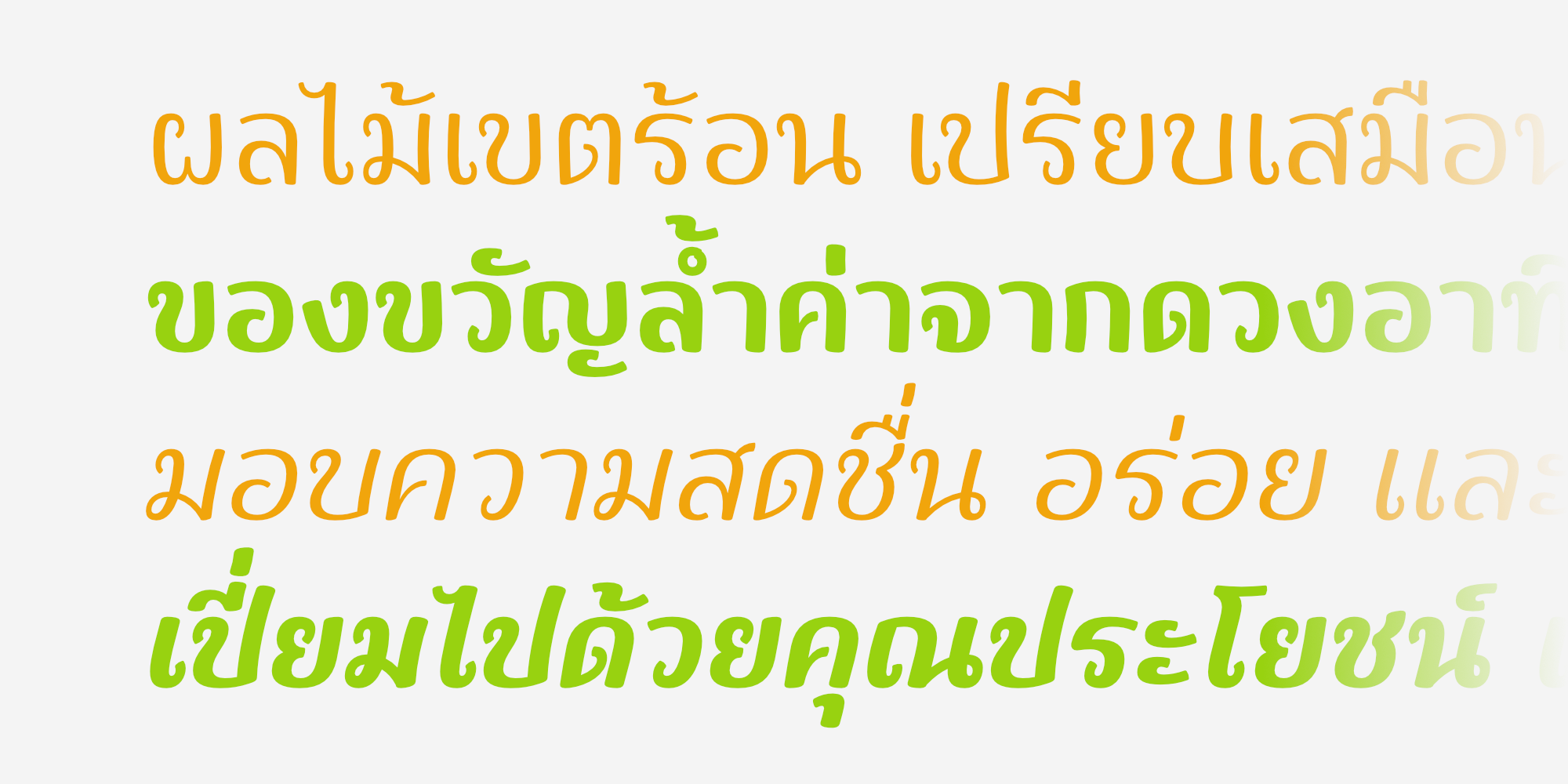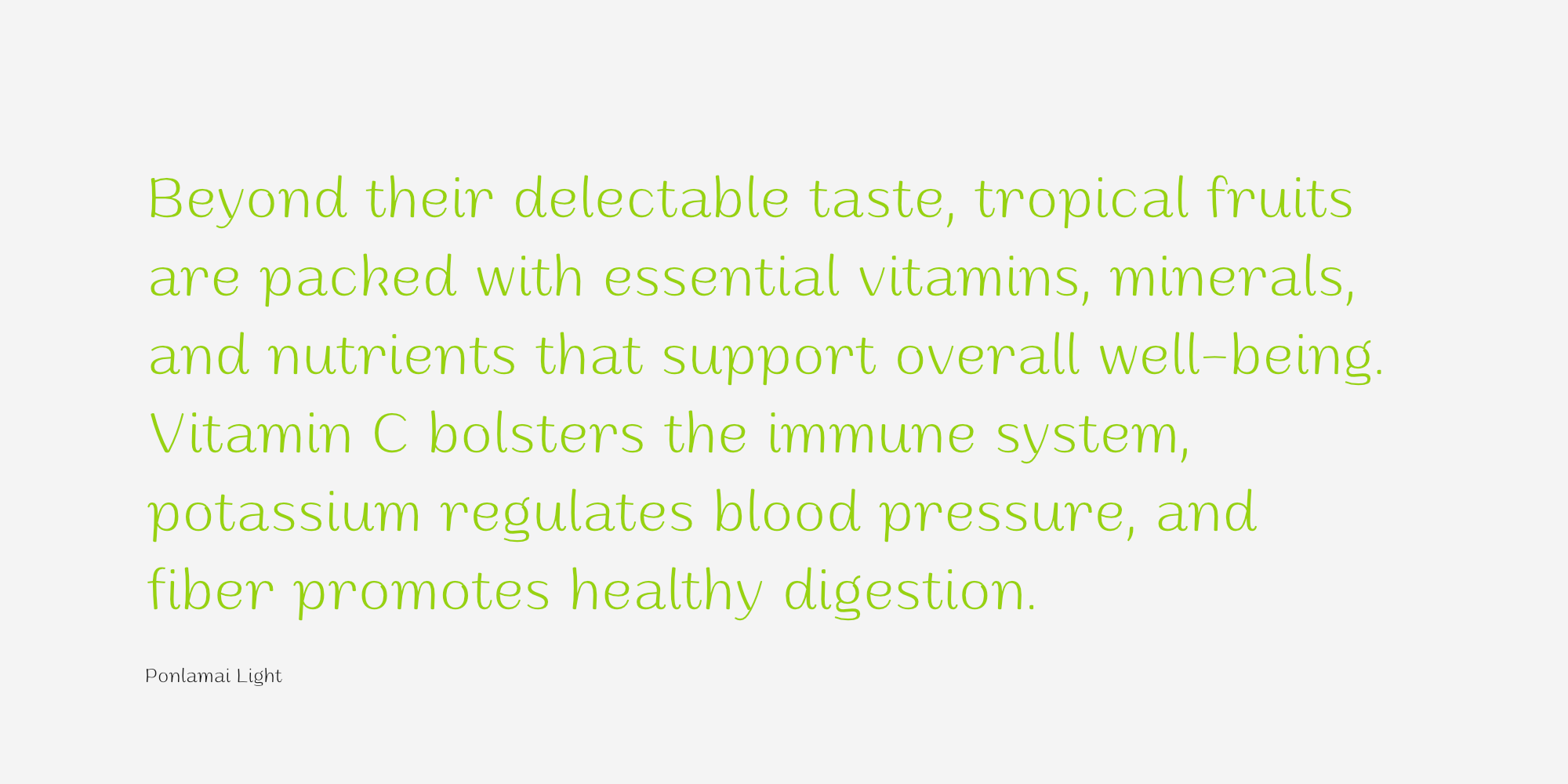
ผลไม้ | Ponlamai
ชื่อฟอนต์ : ผลไม้ | Ponlamai
Ponlamai แบบอักษรสุดชิคที่จะพาคุณเดินทางสู่ตลาดผลไม้สดแห่งความทรงจำ! เหล่าพ่อค้าแม่ค้าตลาดสดนั้นล้วนแล้วแต่เป็นศิลปินเงียบ ๆ ที่ใช้ปากกามาร์กเกอร์วาดสีสันบนป้ายราคา ด้วยการเขียนที่อ่อนช้อยและสไตล์ไม่เหมือนใคร Ponlamai จึงถูกสร้างสรรค์ขึ้นเพื่อเลียนแบบมนต์เสน่ห์นี้โดยเฉพาะ Ponlamai มีให้เลือกใช้ด้วยกันถึง 18 สไตล์ ตั้งแต่ร่างบางพริ้วไหวจนถึงอ้วนอึ๋มอารมณ์ดี รองรับทั้งภาษาไทยและลาติน-1 พร้อมส่งพลังบวกและยิ้มแย้มแจ่มใสไปให้กับทุกสื่อที่คุณสร้างสรรค์ Ponlamai เหมาะสำหรับการสื่อสารแบบสบายๆ ไม่เคร่งครัดจนเกินไป เช่น วีดีโอกินเที่ยวเล่นบนยูทูบ รายการวาไรตี้ สติ๊กเกอร์ หรือสำหรับใช้ตกแต่งบรรจุภัณฑ์อาหาร เครื่องดื่ม ขนม และผลไม้
Creator : อานุภาพ ใจชำนาญ (Anupap Jaichumnan)